<2023년 신년인사 굿즈> 제작기 2
하고 싶은 거 다했어요
<2023년 신년인사 굿즈>는 프로젝트에 참여한 디자이너들이 자율성을 가지고 진행되었습니다. 그래서인지 평소보다 과감한 자세로 임하게 되었는데요. 특히 폰트 디자이너가 아닌 참여자들도 이번 프로젝트를 통해 난생처음 폰트를 만들어볼 수 있어서 의미가 컸습니다. 평소에는 쉽게 도전하지 못하던 것도 함께하니 용기가 생기는 것 같아요. 연초 기획부터 연말 런칭까지, 쉬지 않고 달려온 신년인사 굿즈 제작기를 들려드릴게요.
3월, 2022년은 어땠냐면요
BX팀은 <2022년 신년인사 굿즈> 제작부터 함께하고 있어요. 패키지를 비롯한 인쇄 제작물에 대한 도움을 요청해 주셔서 중간 단계부터 합류하게 되었습니다. 작년에는 어느 정도 작업이 진행되고 있던 상황에 합류했기 때문에 제작물에 대한 도움만 드릴 수 있던 것이 아쉬웠던 점이었어요. 그리고 계획에 없던 제작물들이 추가되면서 전체적인 일관성이 떨어진다는 부분도 개선점이라고 느꼈습니다. 이런 점들을 보완하고자 <2023년 신년인사 굿즈>는 기획 단계부터 BX팀이 함께 하게 되면서 좀 더 체계적으로 진행되었습니다.
<2022년 신년인사 굿즈 > 절기달력
4월, 뭘 만들어 볼까?
<2022년 신년인사 굿즈>는 레터링 작업을 잘 보여주기 위해 달력이라는 매체를 사용했어요. 2023년에는 그 연장선으로 달력에 사용되는 숫자를 베리어블 폰트로 만들어보자는 방향으로 프로젝트가 진행되었습니다. 굿즈 또한 이 방향성에 맞춰 아이데이션을 시작했습니다.
<2022년 신년인사 굿즈> 절기달력 중 한로(寒露)
달력에 담겨 있는 숫자는 ‘기념일’의 의미가 강하다고 생각했습니다. 그래서 2023년에는 평범한 날도 특별한 날도 모두 행복한 날이 되기를 바라는 마음으로 ‘매일매일이 기념일’이라는 메시지를 담았어요. 그 행복한 날들에 산돌이 함께한다는 것을 365일의 달력으로 이야기하고 싶기도 했어요. 이런 흐름으로 굿즈도 기념일에 사용할 수 있으면서 사용자만의 기념일을 표기할 수 있는 고블렛잔으로 결정했습니다.
6월, 디자인 시작!
<2023년 신년인사 굿즈> 프로젝트에 참여하는 디자이너들과 방향성을 공유하고 각 담당 월을 정했습니다. 폰트의 컨셉이 겹치지 않도록 중간중간 모여 피드백을 진행하며 서로 시안을 공유하고 아이디어도 주고받았어요. 굿즈 전체를 관통하는 테마인 ‘기념일’을 중심으로 특별한 날, 계절, 주기 등 다양한 관점으로 해석한 결과물들이 나왔습니다. 각 월의 폰트와 달력 디자인이 궁금하신 분은 전편(링크)에서 상세한 내용을 읽어보실 수 있어요.
제작팀과 기획팀
9월, 첫 번째 고민
연말에 런칭되는 신년인사 굿즈는 산돌뿐 아니라 산돌구름을 통해서도 배포됩니다. 두 브랜드 모두 감사 인사를 전한다는 목적은 동일했지만 산돌은 폰트 파운드리로써 연구적 성격을, 산돌구름은 플랫폼의 특성을 담아야 한다는 점에서 달랐어요. 브랜드 별로 굿즈를 제작할 수 있다면 각 메시지를 더 분명히 할 수 있겠지만 제한된 조건 안에서 방법을 찾아야 했습니다.
먼저 혼란을 최소화하기 위해 두 브랜드의 컬러 외에는 컬러를 모두 배제했어요. 산돌의 레드, 산돌구름의 블루 두 컬러의 적절한 배치를 통해서 산돌과 산돌구름이 공존 가능한 디자인을 찾고자 했습니다. 사용자가 굿즈를 들여다보는 동안 산돌과 산돌구름을 자연스레 연상할 수 있으면 좋겠다는 바람도 담았어요.
구성면에서는 굿즈의 아이템은 동일하게 유지하되 메시지를 직접적으로 전달하는 감사 카드를 달리 만들었습니다.
<2023년 신년인사 굿즈> 달력
<2023년 신년인사 굿즈> 신년인사 카드 (산돌/ 산돌구름)
10월, 두 번째 고민
다양한 폰트의 매력이 잘 드러나면서 하나로 묶어 줄 수 있는 표현 방법이 필요했습니다. 그리고 동시에 숫자 폰트만으로도 재미있는 연출이 가능하다는 것을 보여주고 싶었어요.
여러 가지 아이디어들이 있었는데요. 폰트의 존재감을 보여주는 시안, 다양한 폰트가 어우러진 시안, 굿즈가 직접적으로 표현된 시안 등 다양하게 접근했습니다. 제작팀과 논의한 결과 다양한 폰트들이 섞여있지만 각각의 형태도 재미있게 잘 담아낼 수 있는 방향으로 의견이 모아졌습니다. 연말연초의 시끌벅적함과 분주한 분위기도 잘 담아낼 수 있을 것이라 생각했어요.
<2023년 신년인사 굿즈> 패키지 시안
<2023년 신년인사 굿즈> 패키지 최종 원고
11월, 충격과 공포의 인쇄 감리
드디어 인쇄 감리 단계입니다. 몇 번이나 방문했던 인쇄소인데 매번 떨리는 건 왜일까요? 두근거리는 마음으로 방문했습니다.
인쇄소를 방문하면 기장님께서 사전에 전달드린 팬톤 컬러칩을 보시고 인쇄에 사용할 컬러를 만들어 주시는데요. 농도를 진하게 해주세요, 노란색을 더 섞어주세요. 등 몇 번의 조정을 거쳐 최종 컬러를 확정한 뒤에 본 제작에 들어갑니다. 풀컬러 제작물의 경우 간혹 잉크가 얼룩덜룩하게 나오거나, 종이 조각 등이 롤러에 묻어있으면 하얀 점으로 찍혀서 나올 수 있으니 기장님 옆에 딱 붙어서 꼼꼼하게 확인하는 작업이 필요해요.
결국 우려하던 일이 발생했어요. 인쇄 파일에서 오브젝트가 겹치는 부분을 깔끔하게 제거하지 않으면 아래의 사진처럼 컬러가 레이어드 됩니다. 모니터 상에서 놓친 부분을 인쇄소에서 발견했어요. 이 아티클을 읽는 분들은 저와 같은 실수를 하지 않길 바라요…
눈물 닦고 아직 수습이 가능한 시점이라는 것에 위안을 얻으며 다시 인쇄소를 방문했어요. 8월 달력을 수정하는 김에 9월, 10월도 조금씩 조정을 했습니다. 망점*이 적은 옅은 컬러를 사용하면 화면에서 보이는 것보다 훨씬 대비가 적게 인쇄됩니다. 그래서 화면상에서 원하는 명도보다 조금 더 밝게 작업해야 한다는 기장님의 팁에 따라 컬러 값을 조금 손봤어요. 이번에는 무사히 감리를 마쳤습니다. 수정 작업을 거친 후 9월 달무리 띠 형태와 10월 호박이 선명해진 게 보이시나요? 이후 작업은 이제 제 손을 떠나 인쇄소에 달려있으니 무사히 입고되기만을 기다립니다.
*K10, C50, M100 등등 CMYK 뒤에 붙는 숫자가 바로 인쇄 망점을 수치화 한 것이에요. 숫자가 낮을수록 망점 개수가 적어져 컬러도 옅게 표현됩니다. 인쇄 망점을 1~99% 가지고 있는 컬러를 인쇄 업계에서는 일본식으로 ‘아미(あみ)’라고 표현하기도 해요.
Before / After
12월, 진짜 최종.arw
이제 마지막을 향한 클라이맥스, 제품 촬영만 남았어요. 이벤트 페이지 운영 디자인에 필요한 이미지 촬영이기 때문에 구체적으로 어떤 사진이 필요한지 유관부서와 논의가 필요했습니다. 실제로 굿즈를 사용하는 활용컷과 기념일의 분위기를 잘 보여줄 수 있는 연출로 방향성을 결정했어요. 데코레이션 디테일은 현장에서 잡아가며 촬영하기로 하고 스튜디오로 출발했습니다. 이번 촬영은 산돌 내부 능력자들로 구성된 촬영팀이 함께 했어요. 이른 아침부터 오후 내내 촬영이 진행되었습니다.
계획형 J들이 주축인 촬영팀인지라 계획대로 착착 진행되어 촬영도 무사히 마치고 UX팀에 최종 셀렉본을 전달했습니다. 드디어 제 역할이 끝났네요. 하지만 런칭까지 방심하면 안 될 것 같아요. 끝날 때까지 끝난 게 아니기 때문에 조마조마한 마음으로 진짜 최종을 기다려봅니다.
(앞선 지난한 과정들을 거친 진짜 최종본이 궁금하지 않나요? UX팀이 어떤 방식으로 감사 인사를 전달했을지 링크를 통해 확인해 보실 수 있어요.)
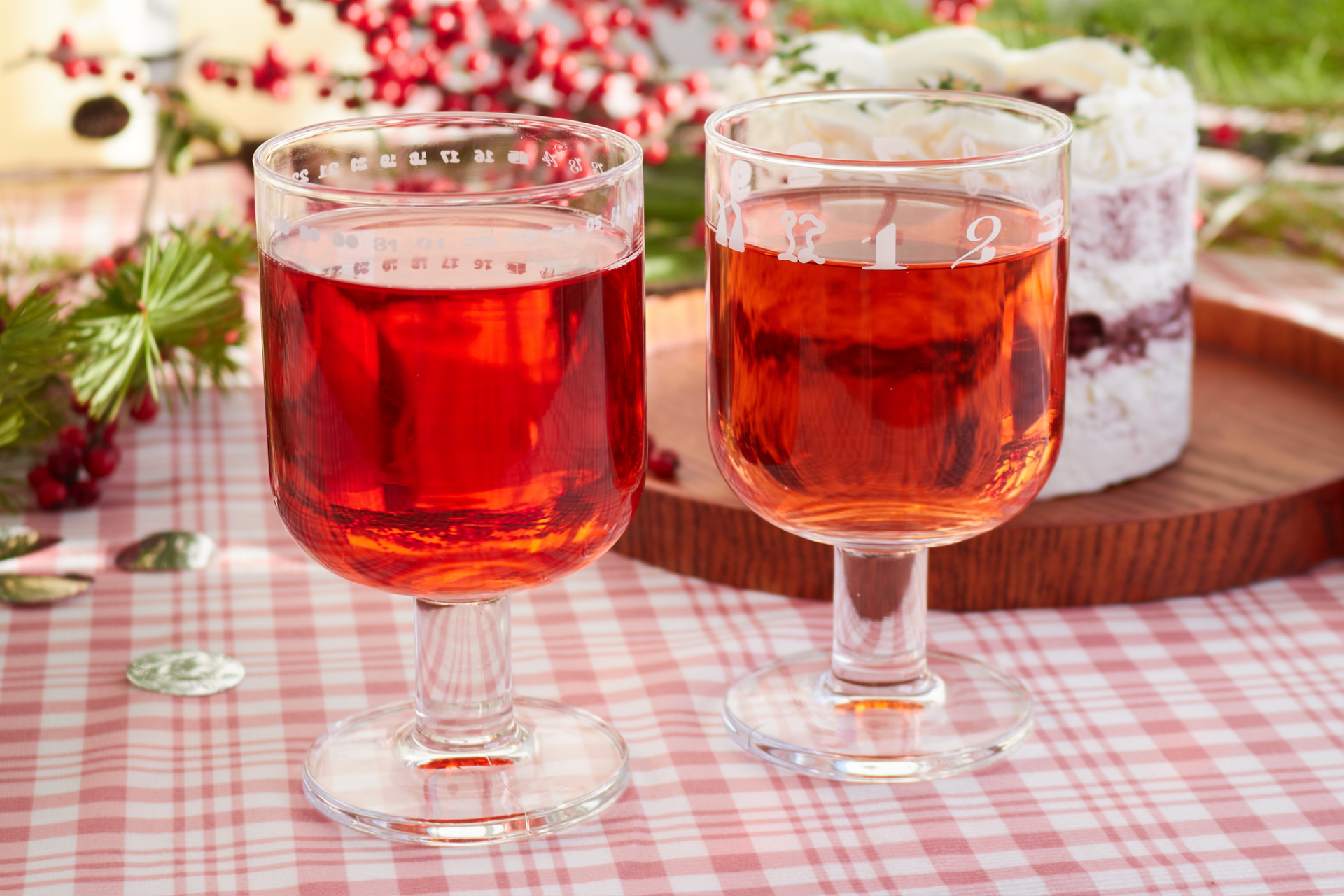
신년이 기다려지는 이유
산돌구름 셀렉샵과의 연계, 굿즈의 물리적 사이즈 등 작년과 비교해 <2023년 신년인사 굿즈>의 규모가 더욱 확대되었습니다. 규모가 커진 만큼 신경 써야 할 부분이 많기도 했지만 배움도 컸던 프로젝트였어요. 서로 도움을 주기도 하고 받기도 하면서 역시 일은 혼자서 하는 게 아니라는 생각을 했어요. 왠지 모르게 아쉬움이 남지만, 신년은 또 오니까요.
모두 행복한 2023년 되길 바라며, 또 만나요!